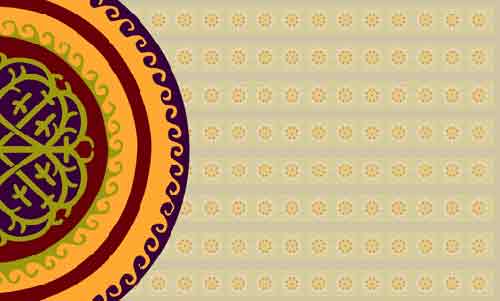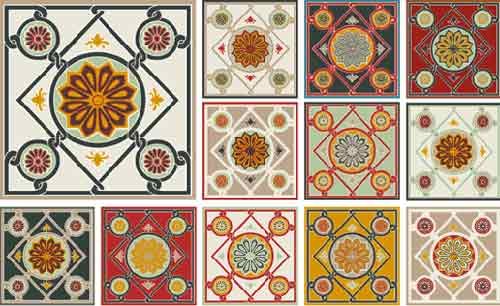
Panos und seine Font-Library Parachute machen wirklich feine Arbeit. Das neue Kind heißt Ornamental Treasures und ist eine Serie von Fonts welche zu wuunderschönen Ornamenten zusammengefügt werden können
PF Ornamental Treasures is a very special series of layered ornamental font families never before released. This is a form of artistic expression which was developed between the 9th and 15th century at the centers of the Byzantine civilization (visit our blogspot to read more historic facts). Unfortunately, these historic treasures were kept from the public eye for centuries. Following an extensive research, Parachute® unearthed these treasures and created an unprecedented series of layered ornaments with great interest to designers, architects, scholars, artists, researchers and students. Each package includes up to 9 fonts (layers) per glyph, which enable the user to create with an unlimited combination of colours in any program, without converting glyphs to outlines. Additionally, several glyphs connect with each other to form banners, frames and exquisite